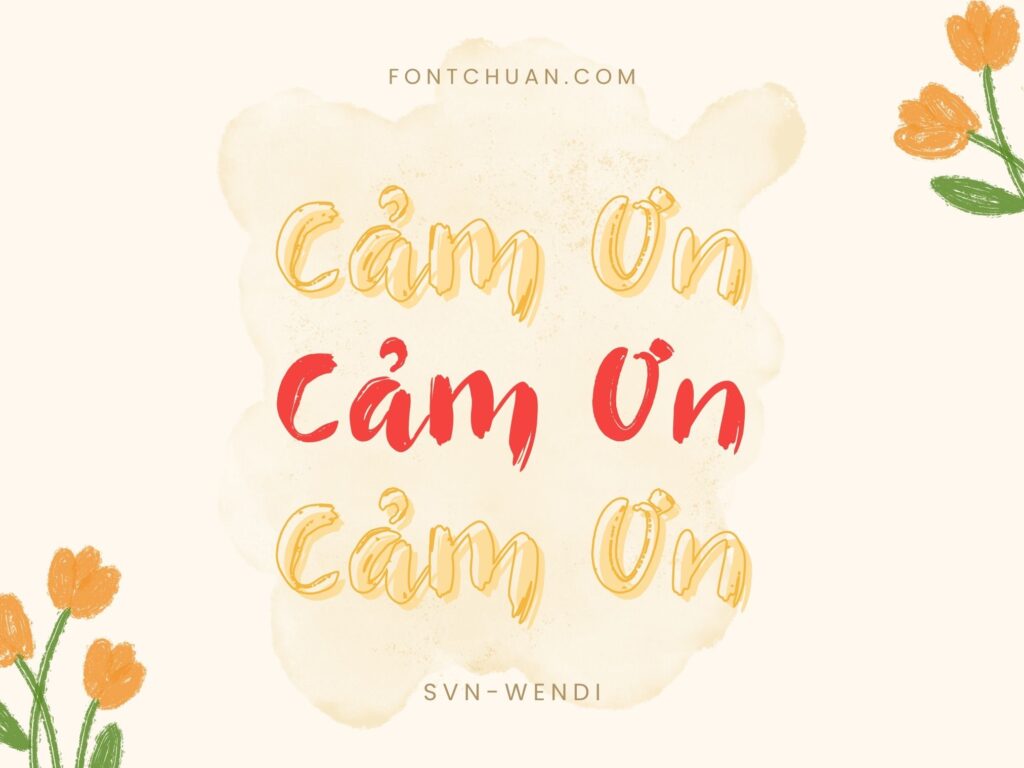
Font SVN Wendi Typeface Việt Hóa
Font SVN Wendi là phiên bản Việt hóa của kiểu chữ Wendi, được thực hiện bởi Styleno.1 Fonts. Wendi thuộc nhóm Font Decorative, mang phong cách viết tay tự nhiên và thân thiện, tạo cảm giác như chữ viết tay thực sự. Font này phù hợp cho nhiều mục đích sử dụng khác nhau, từ thiết kế thiệp mời, tiêu đề đến các ấn phẩm truyền thông, mang lại sự mềm mại và tinh tế cho từng dự án.
SVN Wendi lý tưởng cho các dự án thiết kế yêu cầu sự gần gũi và cá nhân hóa, như thiệp mời, tiêu đề, bao bì sản phẩm và các ấn phẩm quảng cáo. Các ngành nghề như giáo dục, ẩm thực và spa có thể tận dụng font này để tạo điểm nhấn nổi bật trong thiết kế. Ngoài ra, font cũng thích hợp cho các sự kiện như Tết, Giáng sinh, sinh nhật và các lễ hội khác, mang lại cảm giác thân thiện và nghệ thuật.